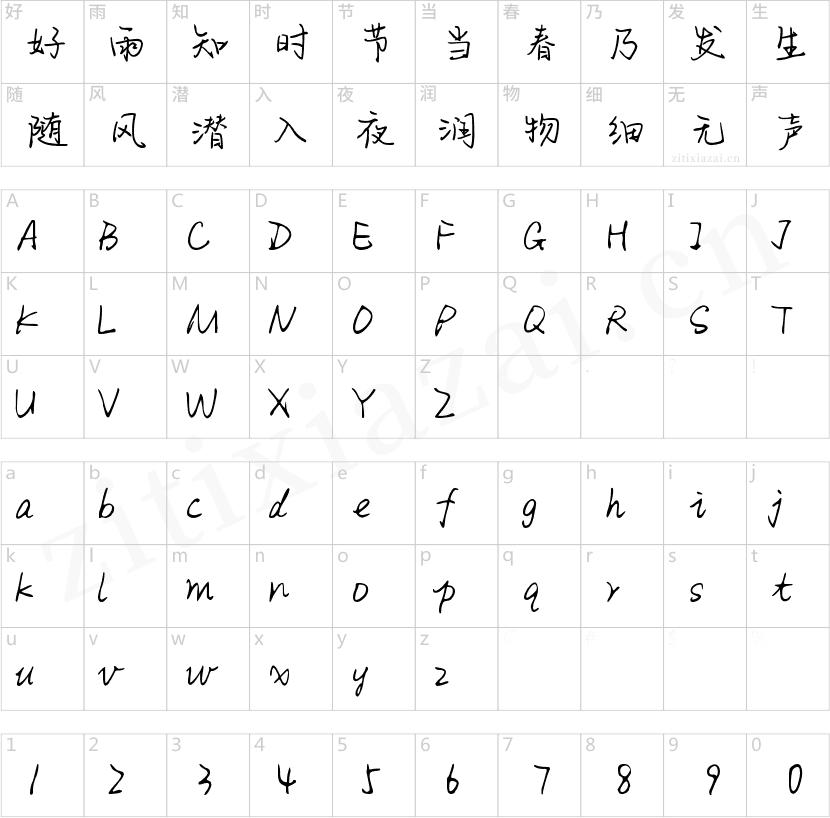
Aa如果我说爱你
Aa如果我说爱你,这款字体结构工整、笔画清晰,兼顾美观与易读性,适用于标题、正文、海报、包装、LOGO 等多种场景。字形优雅稳定,风格百搭耐看,适配日常排版与创意设计,让文字呈现更舒适、更具质感。Aa如果我说爱你一笔一画,皆是细节,以均衡的比例、流畅的线条打造舒适视觉体验,字形端正大气,风格简约现代。无论是商业设计、品牌宣传还是日常排版,都能轻松驾驭,让文字更有格调与力量。Aa如果我说爱你字体下载。
Aa如果我说爱你字体
Aa如果我说爱你是一款非常具有艺术性的字体,它的设计灵感来源于对古典艺术的研究,同时又融入了现代字体设计的元素。字形优美,笔画粗细变化自然,给人以大气、典雅的感觉。Aa如果我说爱你是一款既传统又现代的字体,它的设计充满艺术感,美观大方,实用性也非常强。无论是对于设计师还是对于普通读者来说,都是一种非常不错的字体选择。Aa如果我说爱你适合用于具有艺术感的场合,比如海报、宣传单张、书籍封面等。由于其字形流畅且具有动态感,也适合用于大量的文本排版,如报纸、杂志等。